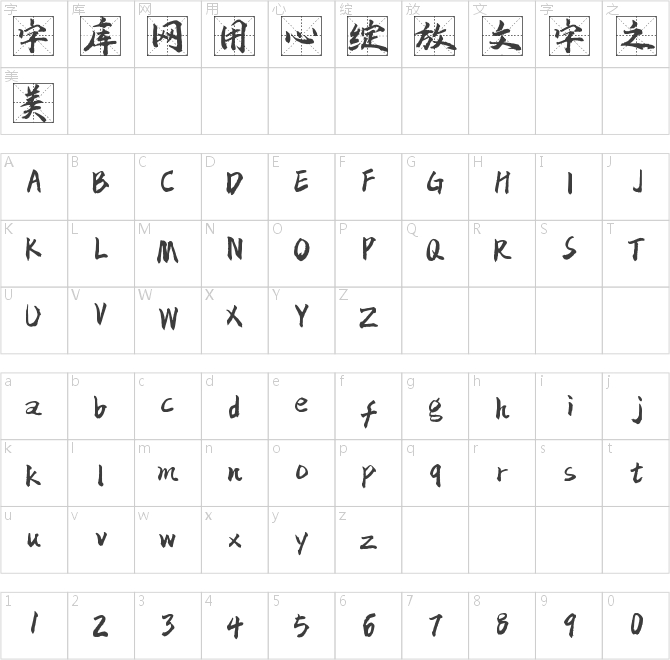
字魂4342號(hào)-白鶴零格字 詳情頁(yè)
字魂4342號(hào)-白鶴零格字字體字庫(kù)是一款讓人賞心悅目、百看不厭的中文字體,適合各類廣告和產(chǎn)品包裝設(shè)計(jì)應(yīng)用,字體大小15.96MB,格式為ttf字體,上傳用戶是星期一,作者/版權(quán)方為字魂